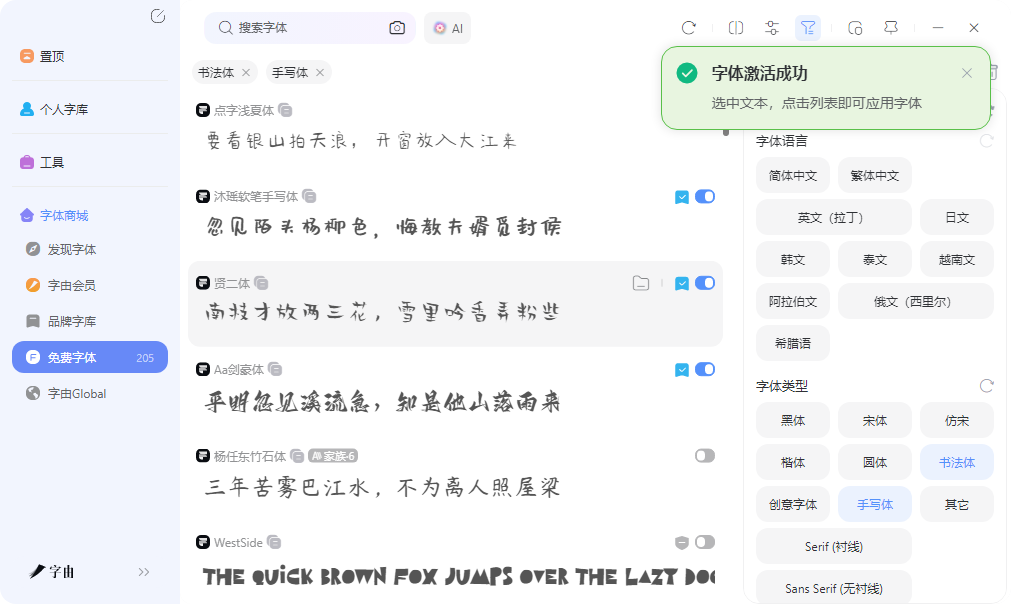
免费设计签名连笔字,不用练字也能写出潇洒签名
俗话说签名是自己的第二张脸,如果在面对一些需要签字的场合,好看的签名是至关重要的。有些人可能会担心自己的字不够好看,练字的话短时间不出效果,那么我可以告诉你现在有很多免费在线工具,输入你的名字,选择喜欢的连笔风格,几秒钟就能生成一张签名图片,直接贴在文档、邮件、简历上。今天实测了5款签名设计工具,每个都有自己的侧重点。有从字体库里挑连笔字的专业方案,也有在线一键生成的花式签名,不论是哪个都能够帮助你设计一款自己喜欢的签名,十分便捷,快来试试吧!
字由虽然本质上不是专门做签名的网站,但字由的字体库里藏着大量适合签名的连笔字体。如果你希望自己的签名不是一张固定的图片,而是随时可以在Word、PS、网页上使用的字体,字由是最合适的方案。
打开字由客户端,在左侧筛选栏里找到“字体类型”,勾选“手写体”或“书法体”。然后筛选“英文(拉丁)”或“简体中文”,再按“免费商用”过滤(如果你做商业用途)。你会看到几十款连笔风格的字体:有的像钢笔流畅连写,有的像毛笔顿挫有致,有的偏现代简约,有的偏传统书法。每款字体都可以实时预览——输入你的名字,比如“张伟”或“Li Ming”,页面立刻显示这款字体写出来的效果。
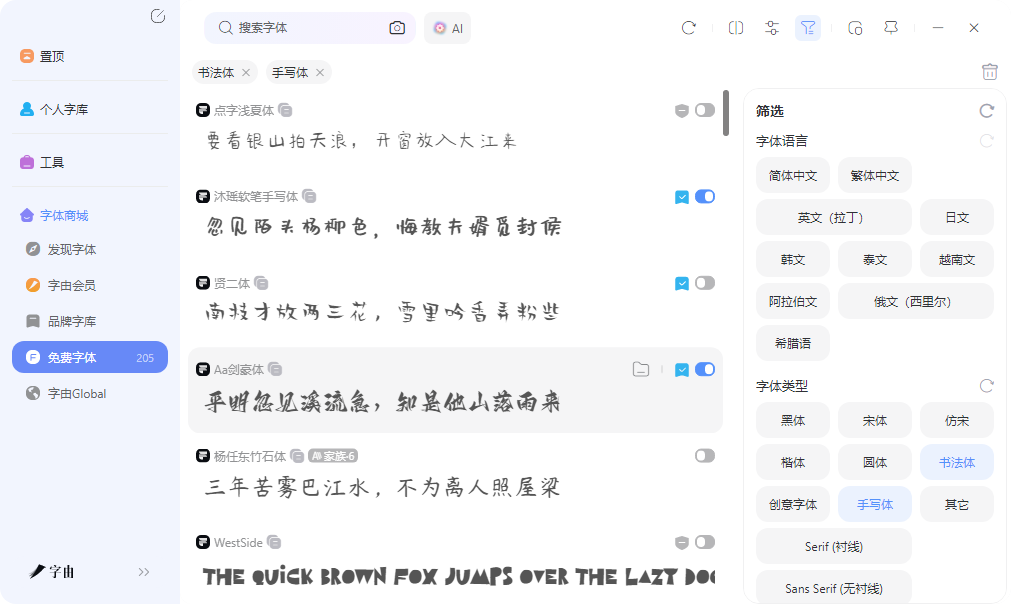
找到喜欢的连笔字体后,点击“激活”。这款字体立刻出现在你的PS、Word、PPT字体列表里。然后你可以在任何软件里打出自己的名字,选择这款字体,就是你的专属签名。而且你可以反复使用,换颜色、调大小、加粗倾斜,自由度比一张固定的签名图片高得多。
另外,字由的AI字体功能也可以用来生成签名图。在AI模板里搜索“手写”“签名”“书法”,找到一款连笔风格模板,输入你的名字,生成PNG图片,背景透明,直接拖进文档里用。如果你不想要安装字体,只想临时出一张签名图,AI字体是更快的路子。
2、连笔字体在线生成站
第二个工具来自一个综合字体转换网站。它的页面里有一个“连笔字体转换器”板块,专门用来生成连笔签名效果。页面上方可以输入文字,下方有“字体预览”区域,展示了“连笔字”示例图片。用户可以选择“迷你简黄草”等字体,调整大小、颜色、背景透明,然后点击“开始转换”,就能生成一张连笔签名的图片。
这个站的优点是操作简单,不需要注册,也不需要下载任何软件。输入名字,选字体,出图,下载。适合那些只需要一张签名图片、不想折腾字体安装的用户。它提供的“迷你简黄草”是一款常见的连笔字体,笔画流畅,适合日常签名。不过需要注意的是,这些字体的商用授权不明确,建议只用于个人非商业用途。如果你只是给自己签个电子名,发个邮件或填个表格,完全够用。
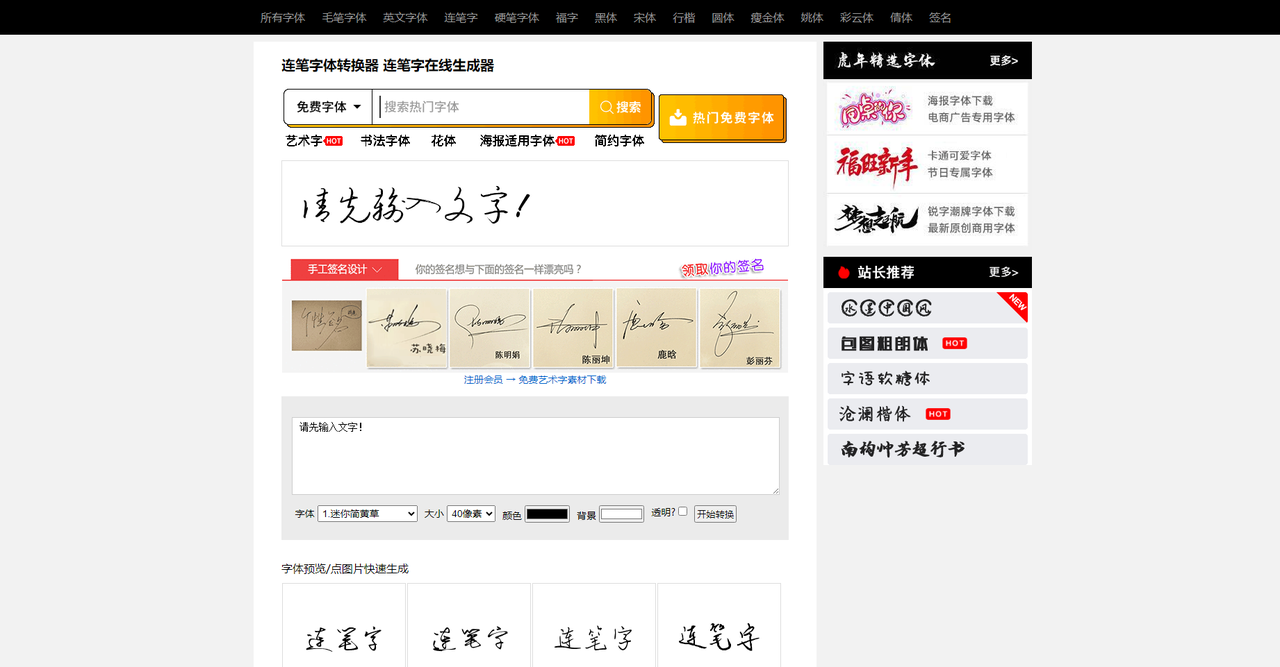
3、AI
第三个网站是AI签名。这是一个AI驱动的在线签名生成器。打开页面,输入你的名字(支持中英文),选择“高级签名”或“普通生成”模式。AI会结合算法生成多种风格的签名方案,用户可以选择喜欢的样式,然后下载为透明PNG或SVG格式。
这个网站的特色在于AI智能设计。它不只是把名字套进字体模板,而是会根据名字的结构和笔画,自动生成连笔、顿笔、倾斜等效果,让签名看起来更自然、更像真人手写。同时,它支持透明背景下载,方便直接粘贴到合同、PDF、邮箱签名中。
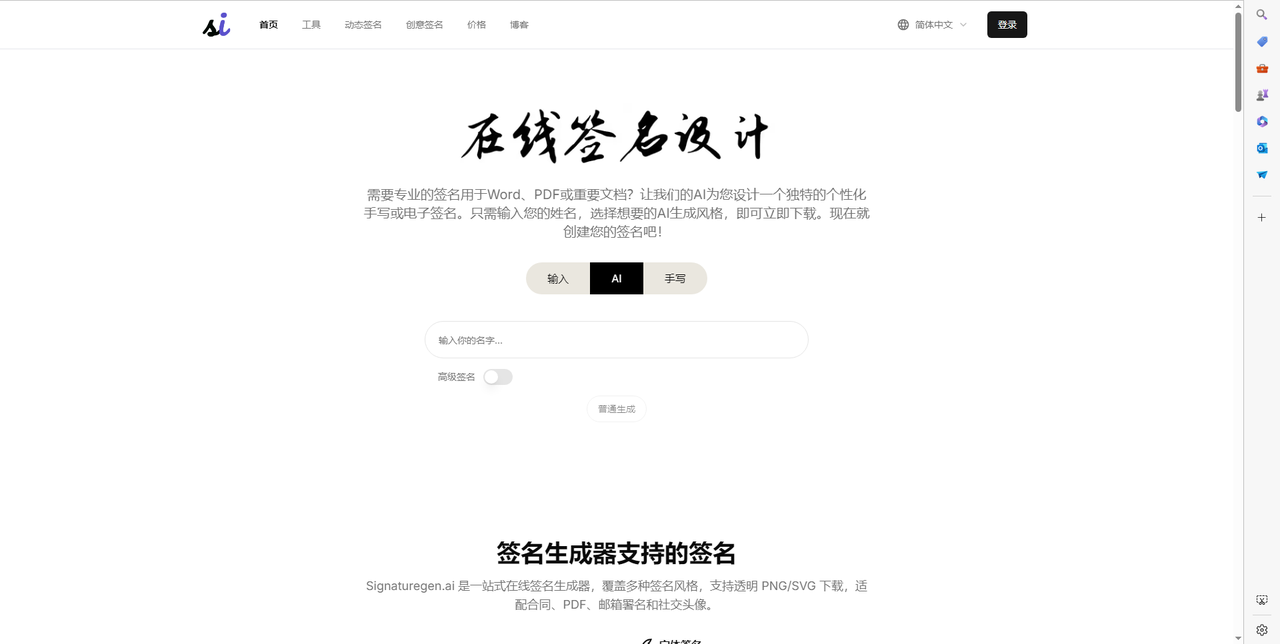
4、gaituba
第四个网站是gaituba,它提供了一个“一笔签名设计”工具。从截图可以看出,这个工具支持多种签名风格:一笔艺术签、连笔商务签、一笔商务签。用户可以输入文本(即你的名字),选择喜欢的风格,然后调节文本颜色、描边颜色、背景色,点击“生成”即可得到签名图片。这个站的特色是风格区分明确。“一笔艺术签”偏向花式、个性化,适合个人社交媒体、手账、创意作品;“连笔商务签”和“一笔商务签”则更加规整、流畅,适合合同、简历、邮件签名等正式场合。用户可以根据自己的需求选择不同风格,还可以自定义颜色搭配,让签名更贴合品牌或个人喜好。
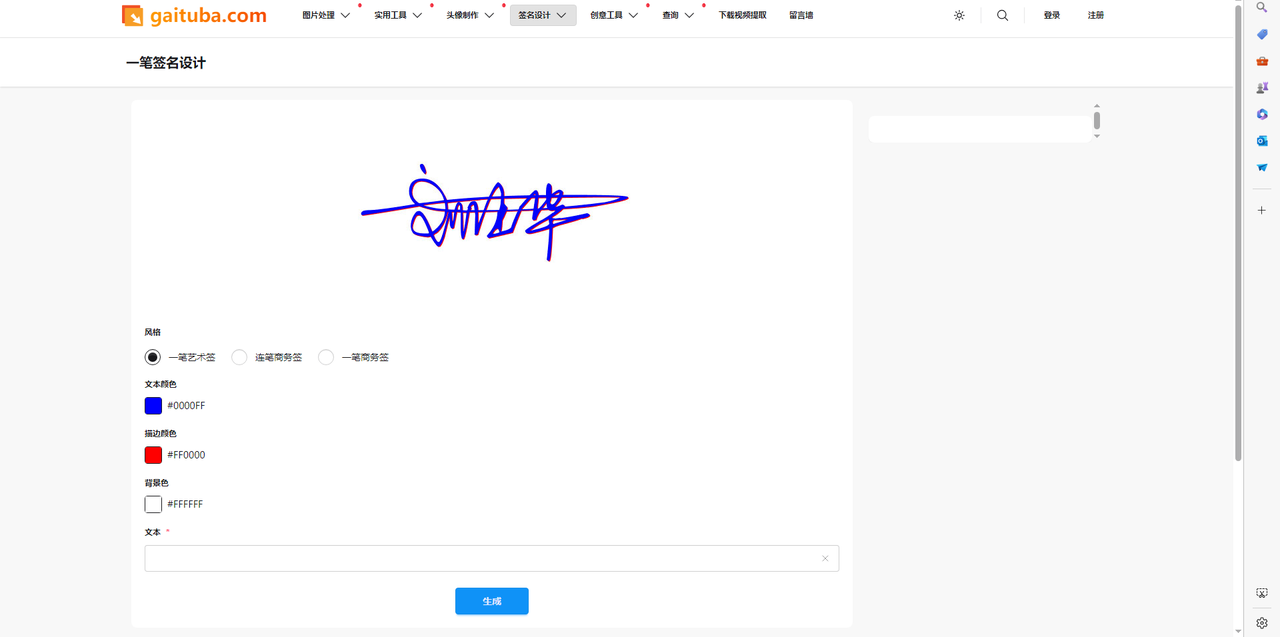
5、艺术字网
第五个网站是艺术字网。它的“连笔公文签名设计”板块专门针对商务公文场景。页面中可以选择“连笔公文签名设计”风格,下方有“笔商务签”等选项。输入名字(例如“杨幂”),点击“给我设计”,系统会生成一张连笔签名图片。还可以调整颜色(字体颜色、背景色等)。
这个站的特点在于它的签名风格更偏向“公文”和“正式”。一笔呵成,线条流畅大气,适合在大量公文文件上使用。页面介绍中提到:“连笔公文签名设计转换器:在商务文件中应用广泛,任何复杂的名字,经过艺术字网相应的简化,一笔呵成,线条流畅大气;尤其是在签名大量公文文件的时候,大大提高了工作效率。”如果你是公司职员、律师、财务等需要频繁签署文件的职业,这个工具能帮你快速生成一个庄重又不失个性的电子签名。
此外,艺术字网还提供了“一笔签名设计免费版在线”“连笔英文签名设计在线生成”等其他签名工具,以及艺术签名设计、姓氏头像等周边功能。它的界面稍显老旧,但功能实用,完全免费。